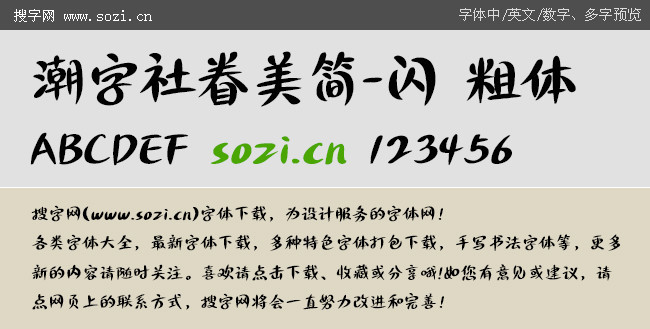
潮字社眷美簡(jiǎn)-閃 粗體
搜字網(wǎng)提供一款潮字社眷美簡(jiǎn)-閃 粗體中文字體下載,潮字社眷美體是一款線條優(yōu)美圓潤(rùn)的藝術(shù)字體,風(fēng)格比一般的字體更有特色,連貫字跡顯得干練而不凌亂,清新簡(jiǎn)明,具有很好的視覺感,適合應(yīng)用于藝術(shù)設(shè)計(jì)、平面宣傳設(shè)計(jì)、網(wǎng)頁(yè)設(shè)計(jì)等領(lǐng)域等應(yīng)用。(本字體為個(gè)人非商用版,商用請(qǐng)聯(lián)系作者購(gòu)買授權(quán))